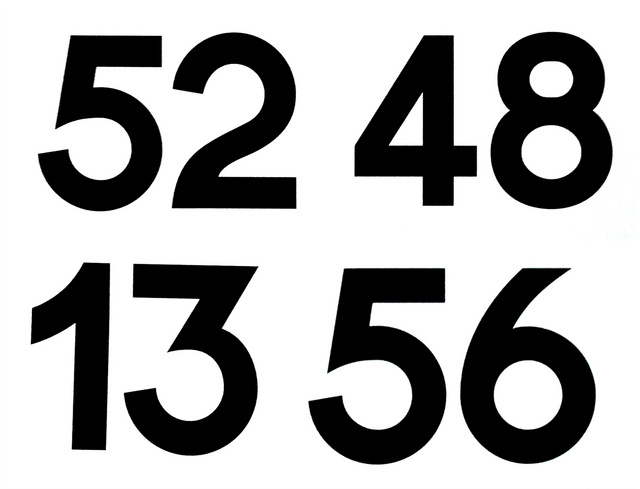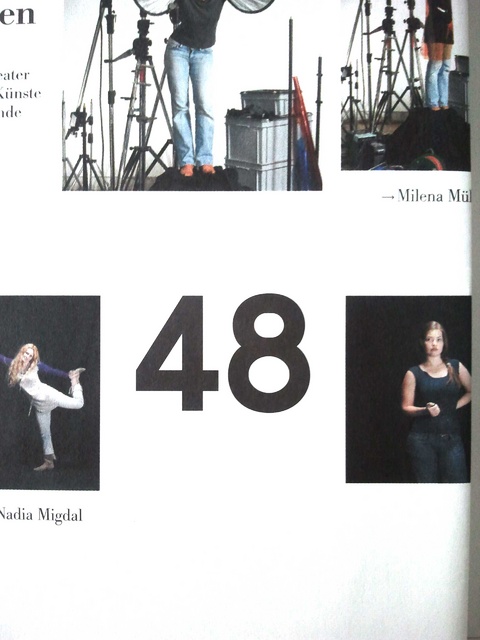
Schrift einer ZHdK Publikation
Diese Zahlen waren so überaschend spitz zulaufend, deshalb sind sie mir bei einer Publikation der Zürcher Hochschule der Künste aufgefallen. Blöderweise habe ich nur die Zahlen fotografiert und nicht den Titel des Heftes. Ich glaube es war ein Jahrbuch/Heft (die Zahlen waren auf einem Faltplakat, das gleichzeitig der Umschlag des Heftes war).
In What The Font und What Font is konnte ich keine ähnliche Schrift finden. Sie könnte von der Avenir oder der Johnston inspiriert sein. Die Rundung, die in die Spitze an der 5 mündet sieht nicht ganz harmonisch aus, deshalb denke ich, dass die Schrift im Studium an der ZHdK entworfen wurde. Vielleicht wurde der Font auch nie veröffentlicht...
Um mir sicher zu sein frage ich euch Profis mal, ob ihr vielleicht diese Schrift kennt.